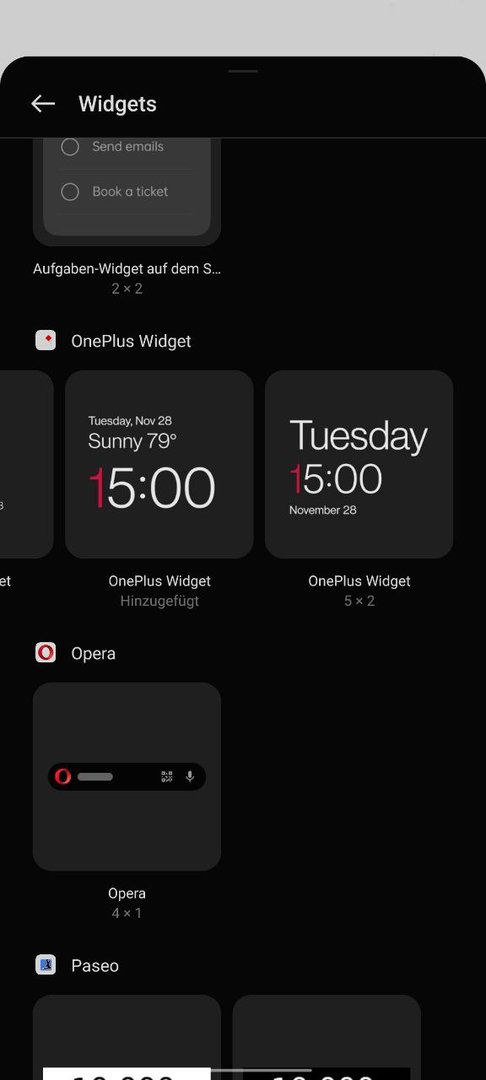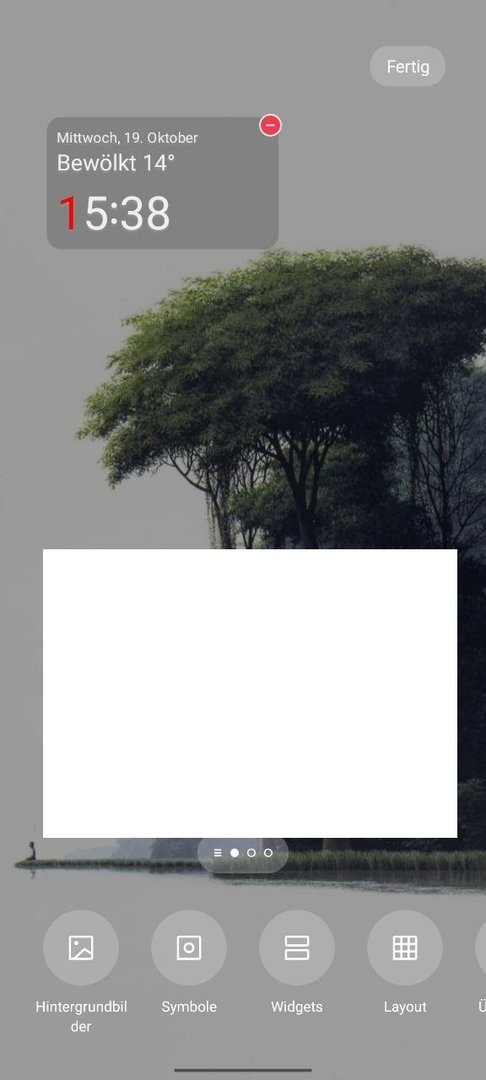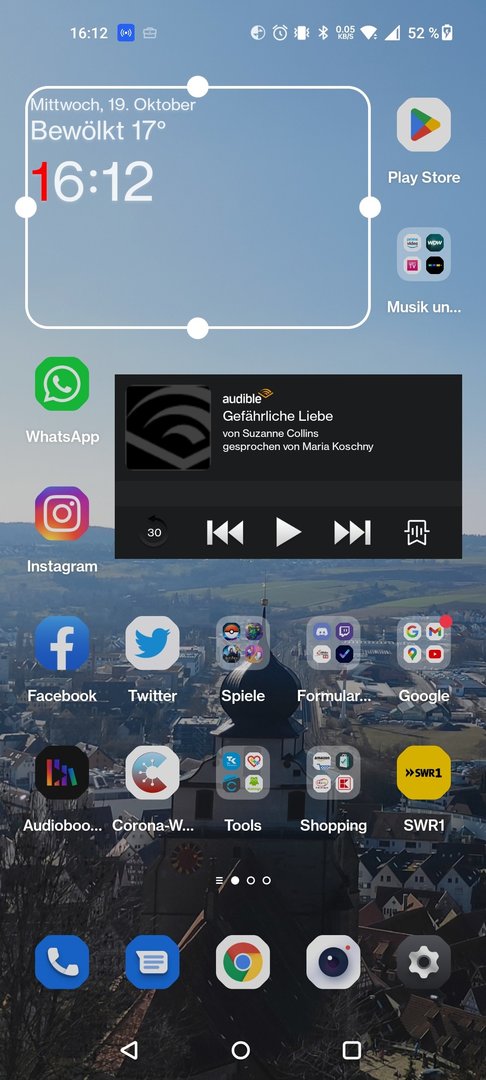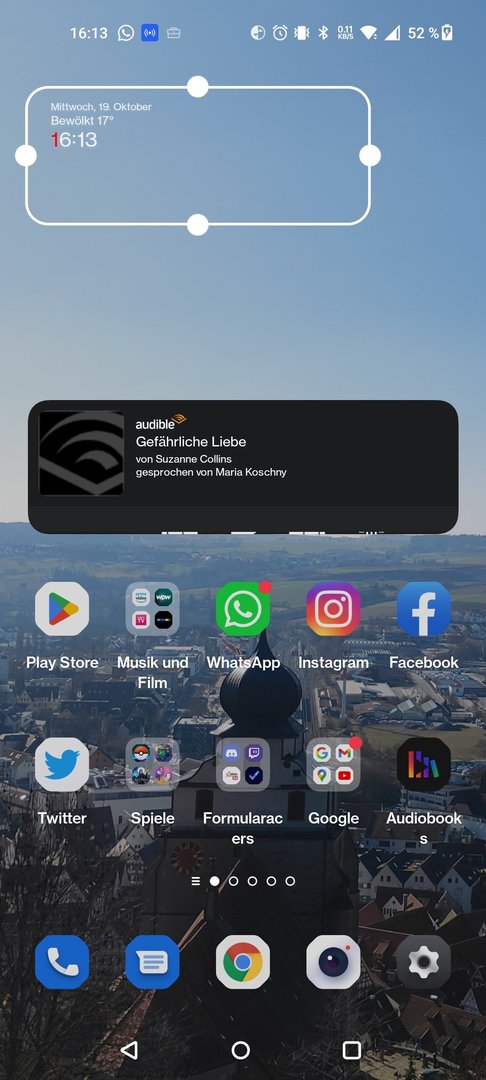
Schriftart ist seit Update DN2103_11_C.10 auf dem OnePlus Nord 2 anders
heute kam das neue Update auf mein Nord 2 5G. Mit den neuen Update und dem längst überfälligen FIX für die Kamera bin ich natürlich super happy.
ABER: Ich find die Unterschrift der Apps und sowieso die Schrift der Uhr etc. ziemlich gewöhnungsbedürftig. Diese war vorher nicht in BOLD. Meldungen vom Oneplus und teilweise Appunterschriften passen nicht mehr in die Reihe, sodass ein Buchstabe in die nächste Reihe rutscht. Das sieht alles sehr bescheiden aus. Hat jemand da Tipps? Habe schon alle Schriftarten ausprobiert und sowieso alles auf Klein gestellt.
Hast du das Handy schon neu gestartet? Benutzt du den original Launcher?
Ich habe mit dem Nova Launcher keine solche Probleme festgestellt.
Genau, Neustart ist schon passiert und ich nutze den Original Launcher. Den Fand ich bisher immer am ansprechendsten. Hab bei externen Launcher immer noch im Kopf, dass die das System extrem ausbremsen.
Ich benutze den Nova schon seit ewigen Zeiten und hatte noch nie Probleme mit großer zusätzlicher Belastung von Android.
Weder bei der Geschwindigkeit, noch beim Akku.
Ich kann den nur empfehlen. Einfach mal in der kostenlosen Version ausprobieren.
@Fischlefreund Dem kann ich nichts mehr hinzuzufügen. Der einzige Launcher den ich kenne, welcher eine Bremse ist/(war?) Ist Samsungs Touchwiz
Ich kann mich @Fischlefreund nur anschließen! Ich nutze den Nova Launcher seit ich das Samsung Galaxy S5 hatte. Der Launcher lief immer stabil und ohne zu Bremsen. Den Standard Lauchner finde ich persönlich etwas dünn von den Möglichkeiten an Einstellungen.
Danke. Aber ich mag das Design vom Oxygen ja. Jedoch ist die Schrift nicht passend siehe Bilder. Selbst in der Widgetauswahl ist die Schrift anders.
@burn0r Das Problem habe ich auch - dachte erst "oh cool, die Schrift zeigt mir, dass es neblig ist", aber die hat einfach überall einen Schatten. Ist auch egal, welche der beiden Schriften und es betrifft nur die Widgets, oder?
Und: welche Rastereinstellung hast du? Bei mir ist das "Uhr" Widget auch völlig durcheinander...
Mir gehts auch maßgeblich um das Uhr-Widget bzw die Schrift. Zusätzlich auch die Unterschriften der Apps. Also das ist alles nicht mehr so "schön" wie vorher. Raster hab ich das ganz kleine und das ganz große ausprobiert. Beides sieht mäßig gut aus.
Normalerweise kann man ja die OnePlus Sans einschalten. Die sollte das ja regeln aber aus irgendeinem Grund wird die nur überall außer auf dem Startbildschirm angewandt.
Es sieht für mich so aus als ob die OnePlus Sans nicht auf dem Homescreen aktiv ist sondern nur Roboto.
Habe das gleiche Problem, neben vielen weiteren Einstellungsänderung seit dem Update, ist die Schrifteinstellung furchtbar.
Also mich hatte es sehr gestört habe auch den Support angeschrieben der hat mir gesagt ich soll mein Handy auf Werkseinstellungen zurück setzten.
@Jannikoks und dann keine Updates mehr machen???
Nein du verstehst mich falsch sie meinten das man das Handy zurück setzten solle auf Werkseinstellungen und dann soll der fehler behoben sein. Trotzdem bleibt Android 12 auf dem gerät. Ich habe es nicht gemacht da es zu viel Aufwand wäre.
@Jannikoks das hatte ich gemacht - keine Änderung bei der Schrift. Egal, ob Handy zurück gesetzt oder nicht.
Dan haben sie mich angelogen.
Hast du gestern das neue Update installiert?
Bei mir war es ein online Update sowas hatte ich noch nie. Weiß jemand was der Unterschied ist?
@Jannikoks
Was meinst du mit Online Update?
Normalerweise kommt es per OTA und wird dir auf deinem Handy angezeigt.